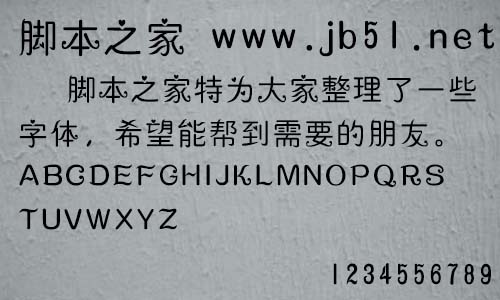
ID心語(yǔ)體簡(jiǎn)是一款中文藝術(shù)字體,這款字體的筆觸較為粗實(shí),字形端莊可愛(ài),一撇一捺勾畫(huà)的十分的細(xì)致,具有很好的視覺(jué)感,適合應(yīng)用于藝術(shù)設(shè)計(jì)、平面宣傳設(shè)計(jì)、網(wǎng)頁(yè)設(shè)計(jì),書(shū)法字帖等領(lǐng)域,需要的朋友可以前來(lái)本站下載。